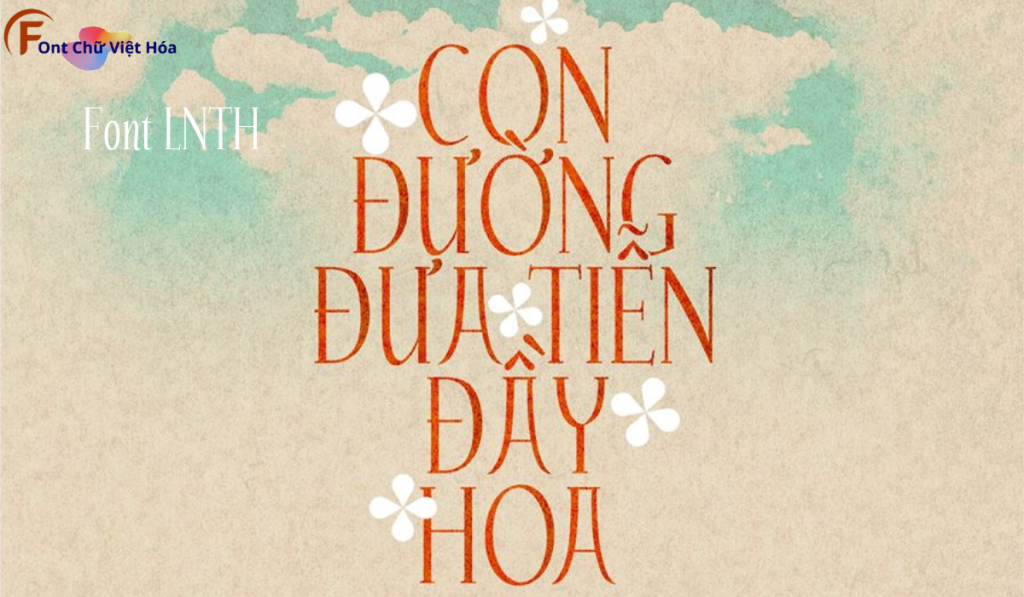
Font LNTH Echelon Việt Hóa
Font LNTH Echelon Việt Hóa là một font chữ hiện đại, thuộc bộ LNTH, với thiết kế sắc nét và tinh tế. Phong cách của font này phù hợp với các dự án thiết kế cần sự chuyên nghiệp và hiện đại, như logo, tiêu đề, hoặc bảng hiệu. Font LNTH Echelon Việt Hóa mang đến sự hiện đại và dễ nhận diện, ứng dụng trong các lĩnh vực sáng tạo. Đặc điểm hình dạng của font bao gồm các đường nét sắc sảo và tinh tế, giúp tăng tính thẩm mỹ và sự chú ý. Việc Việt hóa font giúp người dùng dễ dàng sử dụng trong các thiết kế tiếng Việt, mang lại sự tiện lợi và linh hoạt.